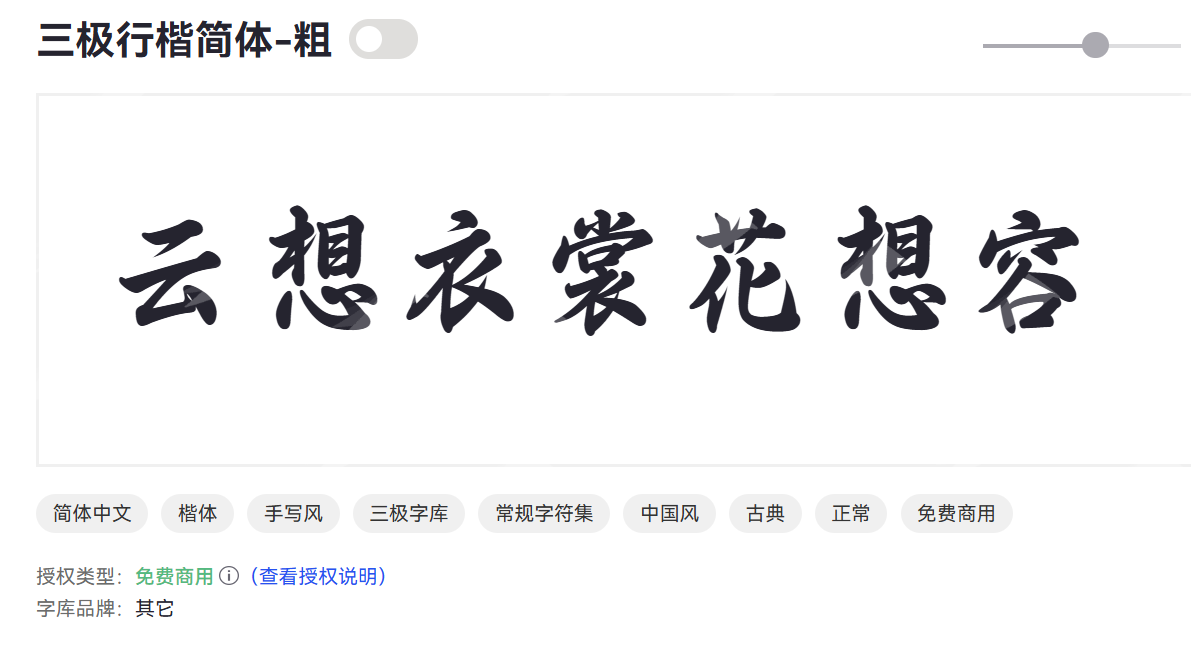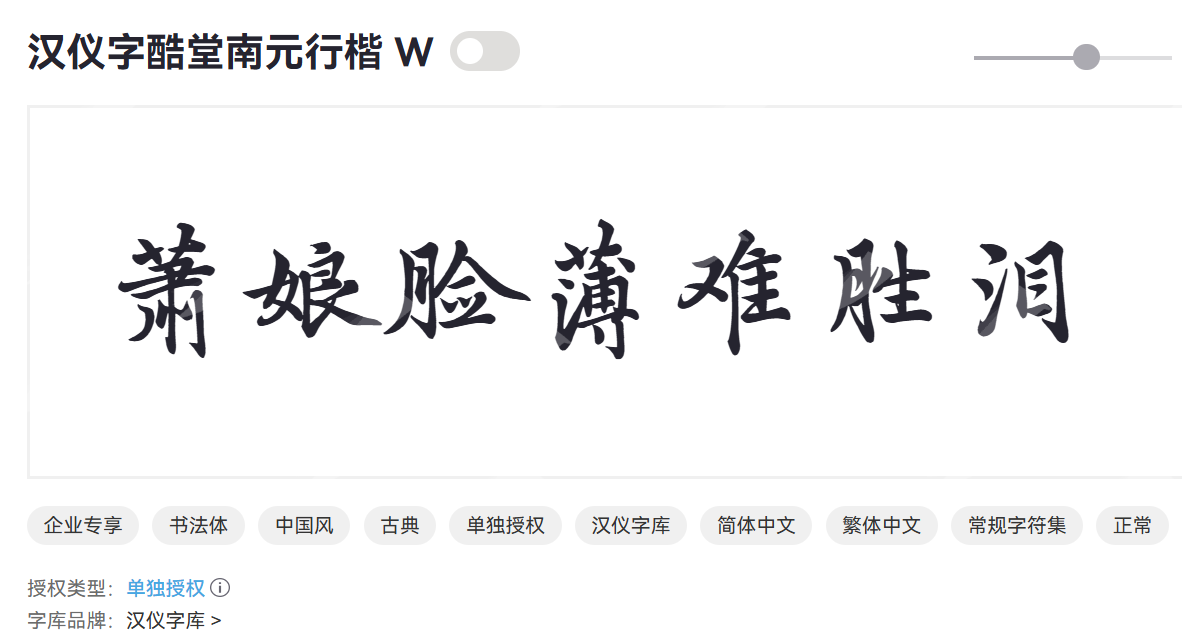
行楷字体大全,免费商用、授权商用、会员商用行楷字体分享
如果你也和我一样,对文字的美感有着一丝执着,那么你一定也会喜欢行楷字体。本文就给大家介绍一下我个人比较喜欢的行楷字体,并且分享 6 款不错的行楷字体,包含了免费的两款、单独授权的两款以及字由会员免费使用的两款。
什么样的字体是行楷字体
行楷是一种介于楷书和行书之间的字体。楷书就像是书法家一丝不苟地描摹每一个笔画,结构端正,而行书则像是行云流水,笔势连绵,充满了动态的美感。行楷呢?它继承了楷书的清晰易读,保留了汉字的结构美;同时又吸取了行书的流畅飘逸。
如果你觉得楷书过于呆板,行书又显得有些难以辨认,那么行楷绝对是一个完美的折中选择。它的笔画或提或顿,或方或圆,既有筋骨,又有神韵,读起来既不费力,又能感受到书写者内心的情感流动。
演示夏行楷
演示夏行楷是一款融合了传统行书的灵动与现代审美的字体。它在保留行书的流畅韵味的同时,也加入了一些现代设计的元素,使其在视觉上更具活力和个性。
字体特点:
- 笔画之间连贯自然,富有动感。
- 结构清晰,易于辨认,不失艺术性。
- 字形大小适中,排版美观。
使用场景:
- 书籍、杂志、海报等印刷品标题和正文。
- 品牌宣传、广告设计。
- 个人作品集、艺术展览。
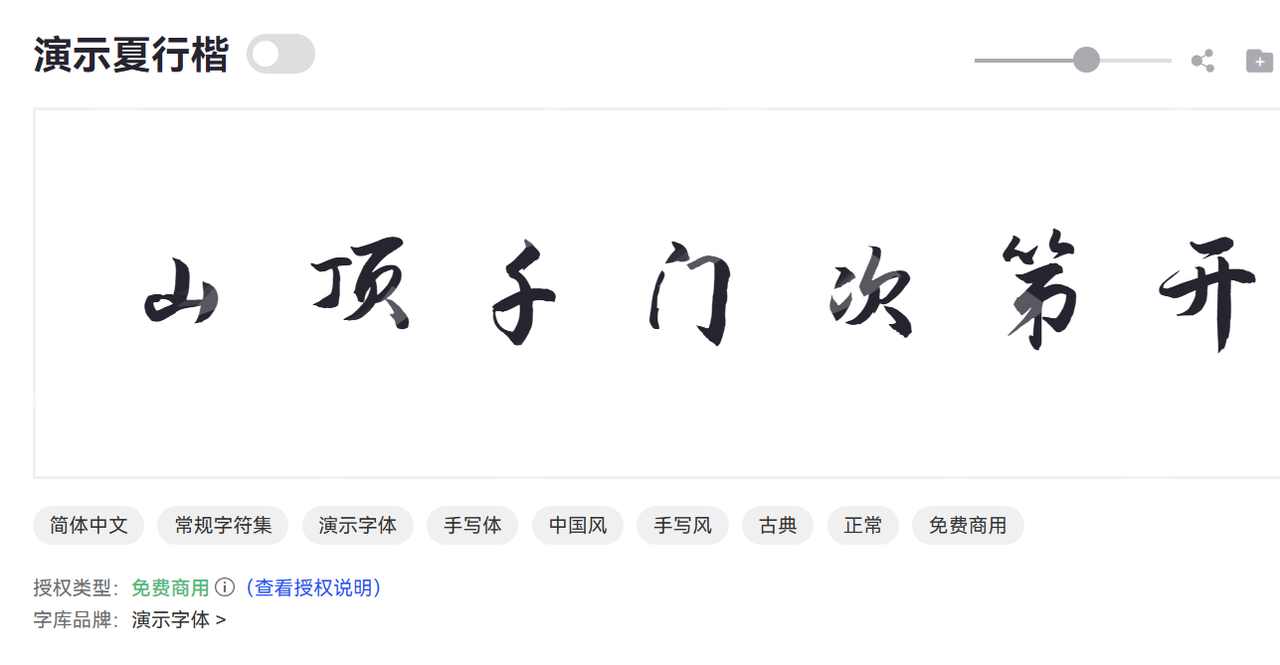
三极行楷简体
三极行楷简体是一款专为中文设计的行楷字体。它以清晰、规范的笔画和均衡的结构为主要特点,力求在艺术性和实用性之间取得平衡。
字体特点:
- 笔画粗细适中,硬朗而不失圆润。
- 字形端正,结构严谨,具有较强的规范性。
- 线条流畅,节奏感强,易于阅读。
使用场景:
- 办公文档、公文、报告。
- 网站、APP界面设计。
- 教育出版物、学术论文。
汉仪字酷堂南元行楷
汉仪字酷堂南元行楷是一款充满个性的艺术化行楷字体。它在传统行楷的基础上,融入了独特的创意设计,使其在视觉上具有强烈的冲击力和辨识度。
字体特点:
- 笔画变化丰富,富有张力。
- 字形设计巧妙,具有独特的韵律感。
- 整体风格洒脱,不拘一格。
使用场景:
- 时尚品牌、潮流设计。
- 活动海报、宣传单页。
- 音乐、电影等娱乐行业相关设计。
- 需要突出个性和艺术感的广告宣传。
汉仪心海行楷
汉仪心海行楷是一款柔美、飘逸的行楷字体。它如同心海般起伏,笔画细腻,流畅自然,传递出一种温婉、优雅的意境。
字体特点:
- 笔画纤细,线条柔和。
- 字形舒展,结构灵动。
使用场景:
- 婚庆、情感类产品包装和宣传。
- 女性时尚、美妆、护肤品品牌。
- 咖啡馆、茶庄等文艺场所的宣传品。
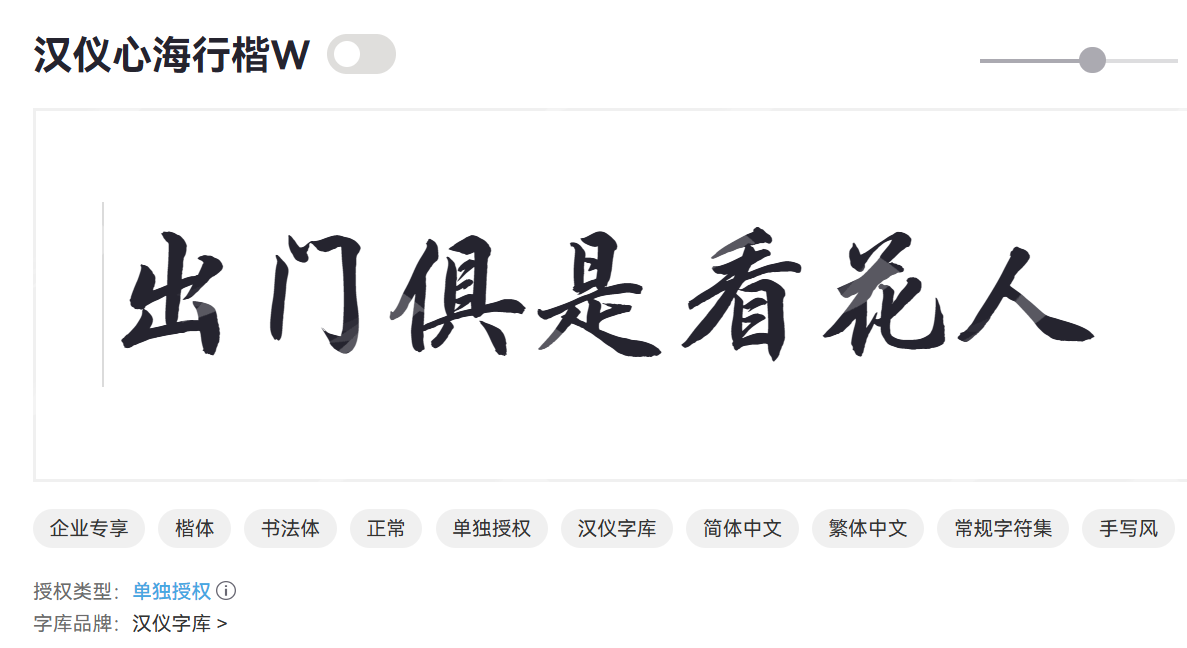
字家惜别行楷
字家惜别行楷是一款带有故事性和情感色彩的行楷字体。它在笔画的起承转合中,蕴含着一种淡淡的离愁别绪,同时又不失行书的洒脱。
字体特点:
- 笔画粗细对比明显,富有节奏感。
- 字形略显瘦长,结构紧凑而富有变化。
- 整体风格带有怀旧、文艺的气息。
使用场景:
- 文艺类书籍、杂志封面。
- 怀旧主题的活动、展览。
- 情感故事、电影宣传。
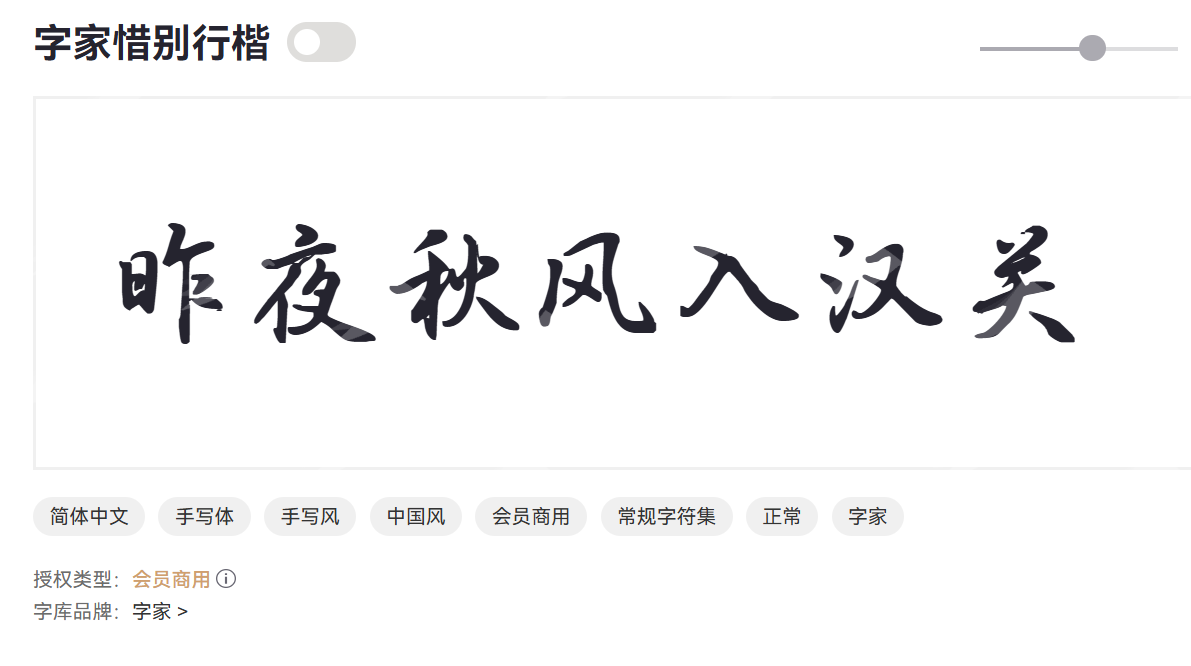
点字禄军行楷
点字禄军行楷是一款结构严谨、笔画清晰的行楷字体。它在保持行楷的飘逸感的同时,更加注重字形的稳健和规范,易于识别和阅读。
字体特点:
- 笔画粗细适中,线条流畅而富有力量。
- 字形方正,结构稳定,不易产生歧义。
- 整体风格沉稳、大气,具有一定的庄重感。
使用场景:
- 商务演示、合同文本。
- 公司官网、企业宣传册。
- 科技、金融类产品的设计。
- 需要清晰传达信息的各类媒体。